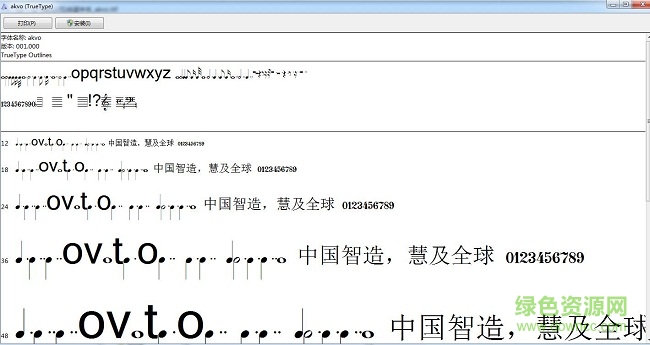
akvo怎么用?五線譜字體(akvo.ttf)是一款特別的電腦字體,輸入數(shù)字和字母就可以顯示出五線譜,同時(shí)用戶還可以自己調(diào)節(jié)各個(gè)音符的距離和大小,需要的朋友快來下載吧!
該字體采用了五線譜構(gòu)造,用戶只需依次輸入0-9、a-z即可輸出五線譜,主要可用于五線譜的排版、平面設(shè)計(jì)等領(lǐng)域!
五線譜是目前世界上通用的一種記譜法,通過在五根等距離的平行橫線上標(biāo)以不同時(shí)值的音符及其他記號(hào)來記載音樂,屬于運(yùn)用最廣泛的樂譜之一。